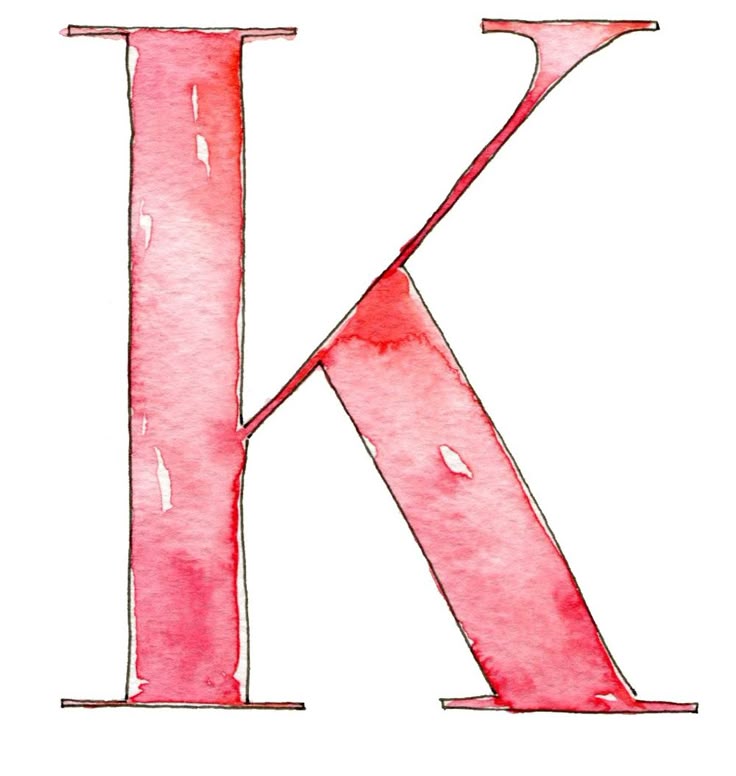
30 великолепных акварельных шрифтов, которые превратят ваш текст в произведение искусства
Тонкие, изящные мазки с прозрачными пигментами, которые захватывают много света. Акварельное искусство, похоже, в последнее время пользуется большим вниманием благодаря художникам в социальных сетях. Также нет недостатка во вдохновении — от пейзажей, персонажей супергероев до космоса, городских пейзажей и флоры.
Но использование этого носителя не ново. На самом деле, он существует с древних времен.
Краткая история акварельной живописи
Метод акварельной живописи восходит к периоду палеолита, когда наши предки рисовали на стенах пещер. Он процветал в средние века, когда медиум использовался для создания религиозных сцен.
Акварельных красок тогда не было. Пигменты, которые в основном были из минералов или растительных волокон, измельченных в порошок, смешивались с яйцом или камедью для создания сюрреалистических произведений. Бумага еще не была идеальной, поэтому художники использовали пергамент, который делали из кожи животных.
Акварельная живопись получила распространение где-то в 16-17 веках. Были произведены более качественные пигменты, но поскольку бумага все еще не была белой, к краскам приходилось смешивать «белую подложку» (например, слоновую кость), чтобы картины выделялись.
27. California Jackpot — это состаренные акварельные шрифты с глифами в обычном, наклонном и рукописном стилях. Он идеально подходит для громких сообщений и привлекающего внимание дизайна!
28. Originals Набор акварельных шрифтов Originals полностью ручной работы и напоминает старые работы битников и фильмы 19-го века.